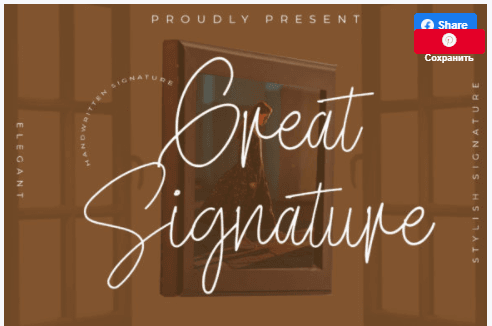
Great Signature Font
Great Signature - приятный, спокойный и тонкий буквенный шрифт. Его можно использовать для различных целей, таких как логотипы, приглашения на свадьбу, заголовки, футболки, фирменные бланки, вывески, этикетки, новости, плакаты, значки и многое другое.